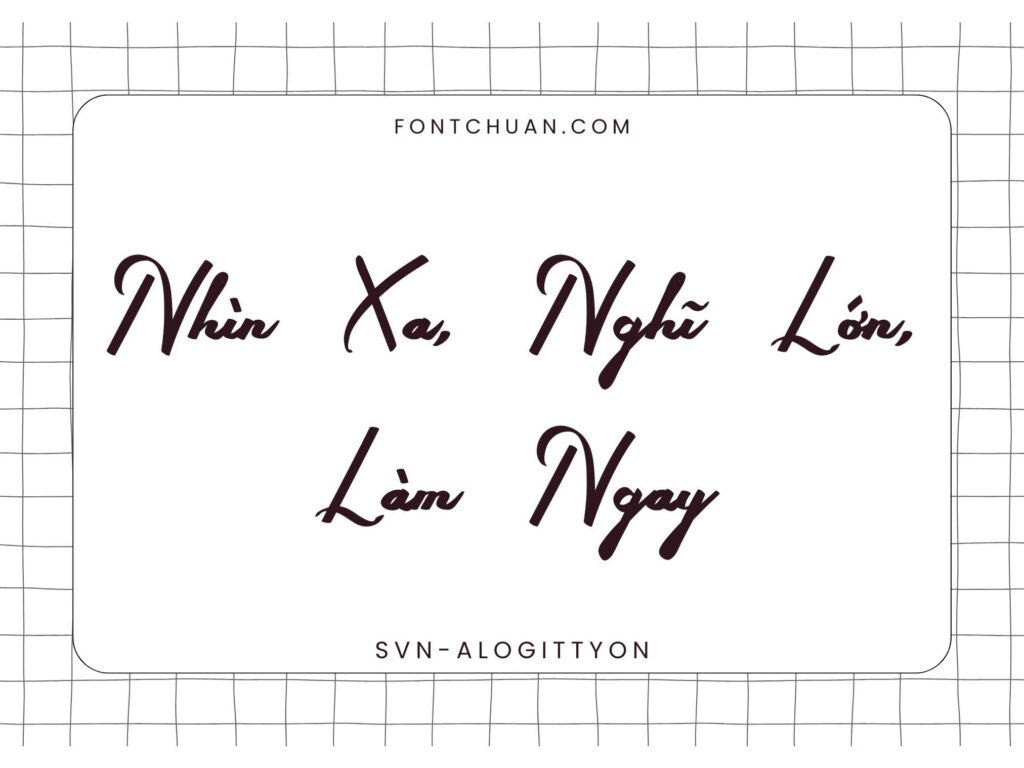
Font SVN Alogittyon Việt Hóa
Alogittyon là một font chữ viết tay độc đáo, mang phong cách hiện đại và tinh tế. Font này được thiết kế với các đường nét mềm mại và uyển chuyển, tạo nên sự thanh lịch và thu hút. Alogittyon phù hợp cho nhiều mục đích sử dụng như thiết kế logo, thiệp mời, tiêu đề, áo thun và các dự án sáng tạo khác. Với hơn 200 ký tự hỗ trợ đa ngôn ngữ, font này cung cấp sự linh hoạt cho các nhà thiết kế trong việc tạo ra những tác phẩm độc đáo. Font đã được Việt hóa để hỗ trợ tiếng Việt bởi Styleno.1 Fonts, đồng thời hỗ trợ nhiều ngôn ngữ khác, giúp mở rộng phạm vi sử dụng trên toàn cầu. Font này được thành viên của Font Chuẩn sưu tầm và chia sẻ, đáp ứng nhu cầu của bạn đọc và ứng dụng thực tế vào các dự án thiết kế.
Đặc điểm thiết kế của Alogittyon bao gồm cấu trúc chữ mềm mại, độ tương phản nhẹ và các đường nét uyển chuyển, tạo nên sự thân thiện và thu hút. Font này phù hợp cho các ứng dụng như thiết kế thiệp mời, tiêu đề, áo thun và các sản phẩm quảng cáo. Các ngành nghề phù hợp bao gồm quảng cáo, sự kiện, giáo dục và nghệ thuật.